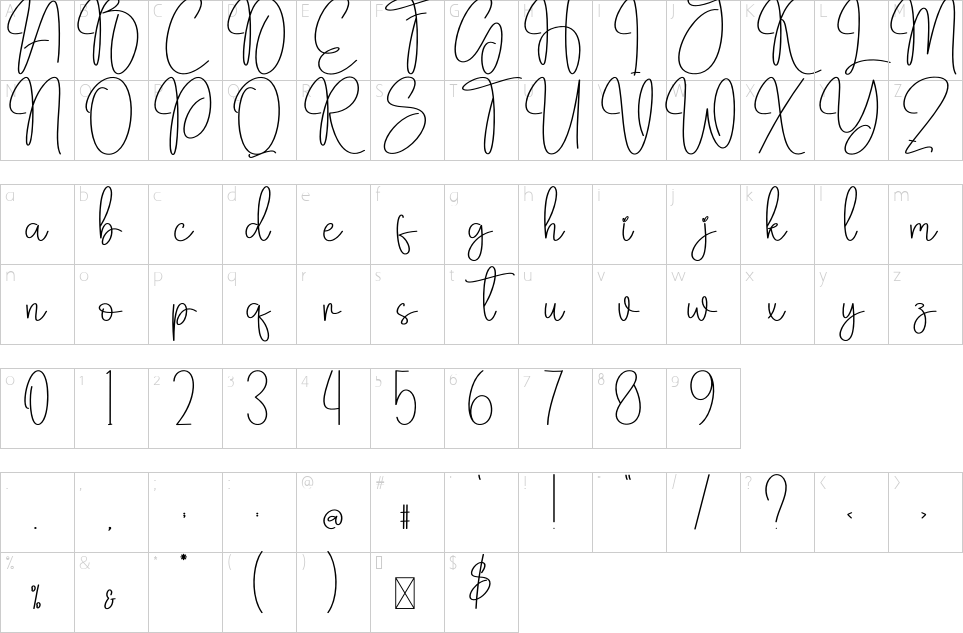
Angela Signature Font – Download Grátis
Descubra a elegância única da Angela Signature, uma fonte ideal para criar textos elegantes e sofisticados. Desenvolvida por scratchones, esta fonte gráfica vem em versões para Windows e Mac. Seu design minimalista, combinado com linhas leves e elegantes, é perfeito para gráficos e criações digitais. Seja para aplicativos de design de software, materiais impressos ou até mesmo para criação de websites, a Angela Signature não se cansa de preencher espaços com seu charme. Convidamos você a experimentar esta fonte única, que já foi baixada 665 vezes, para experimentar seu diferencial na sua próxima criação.